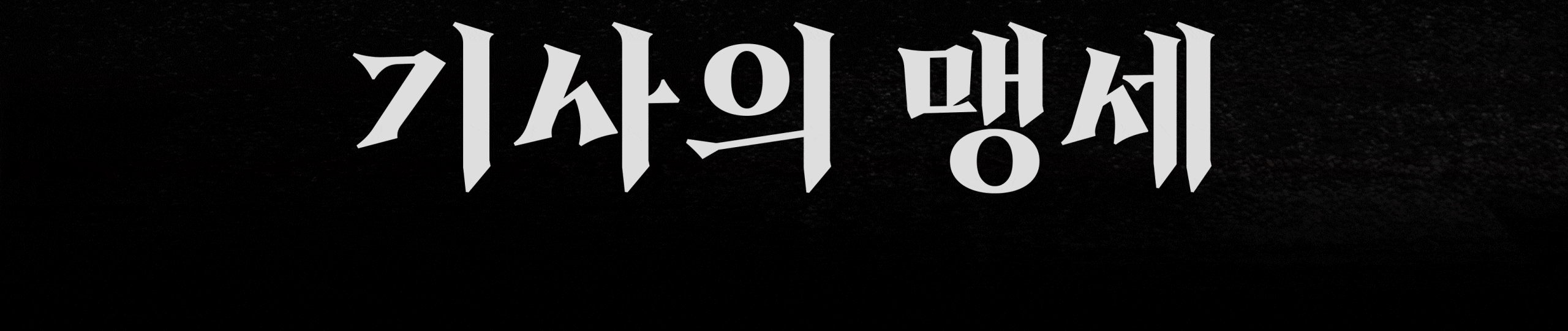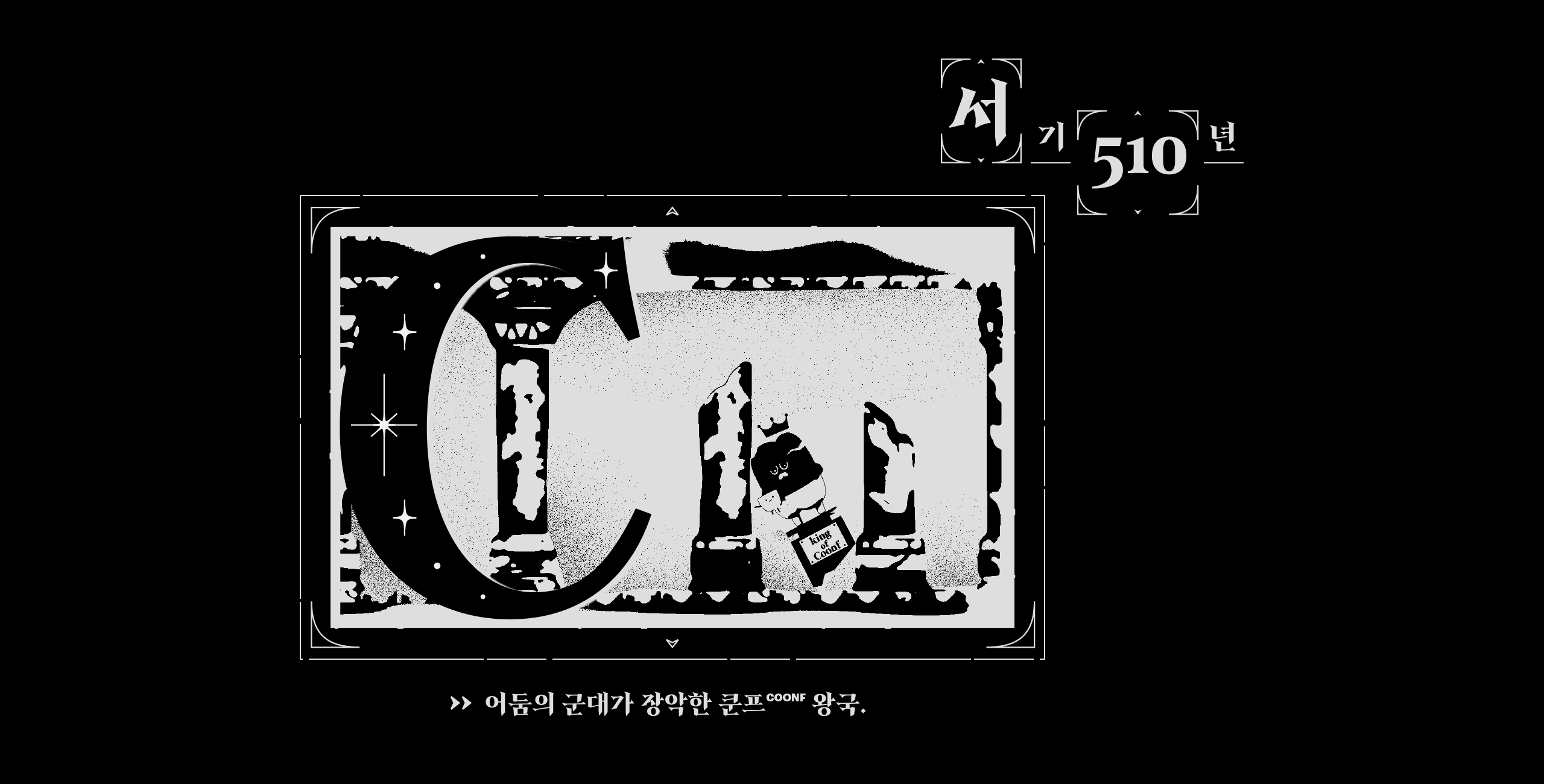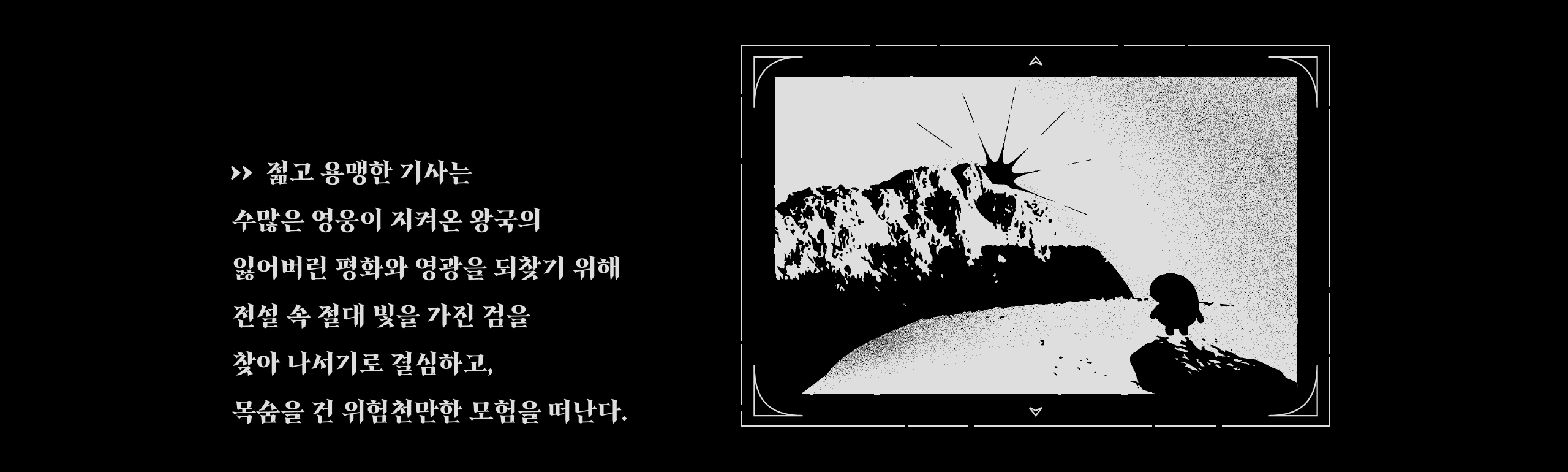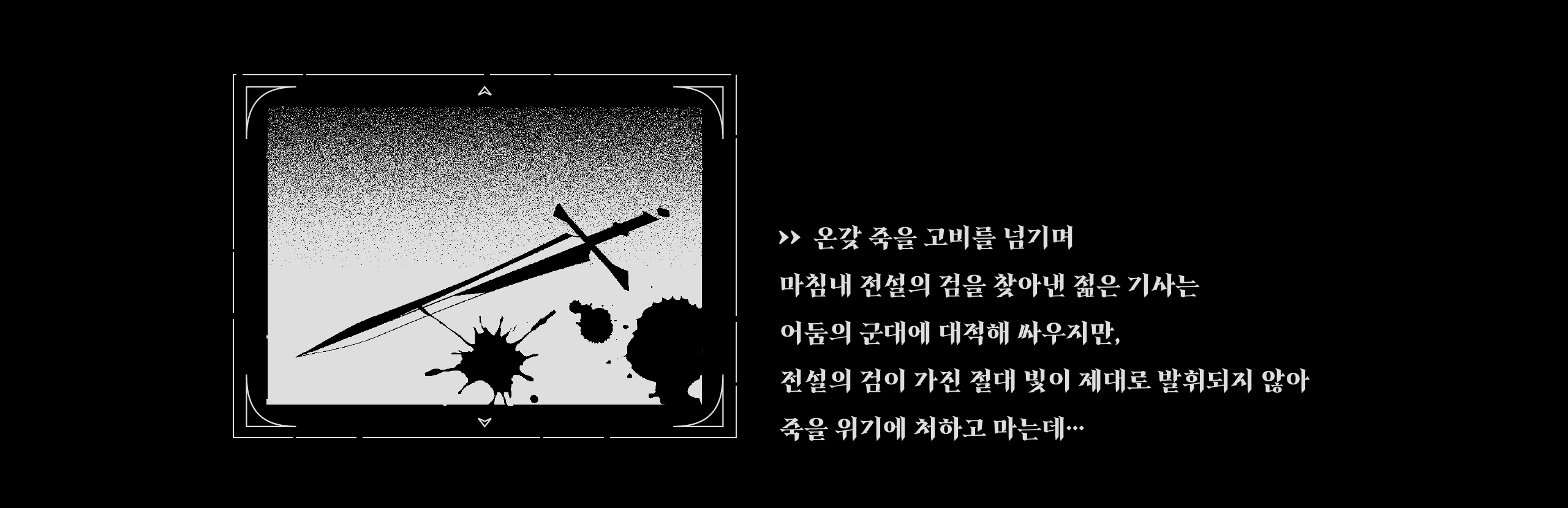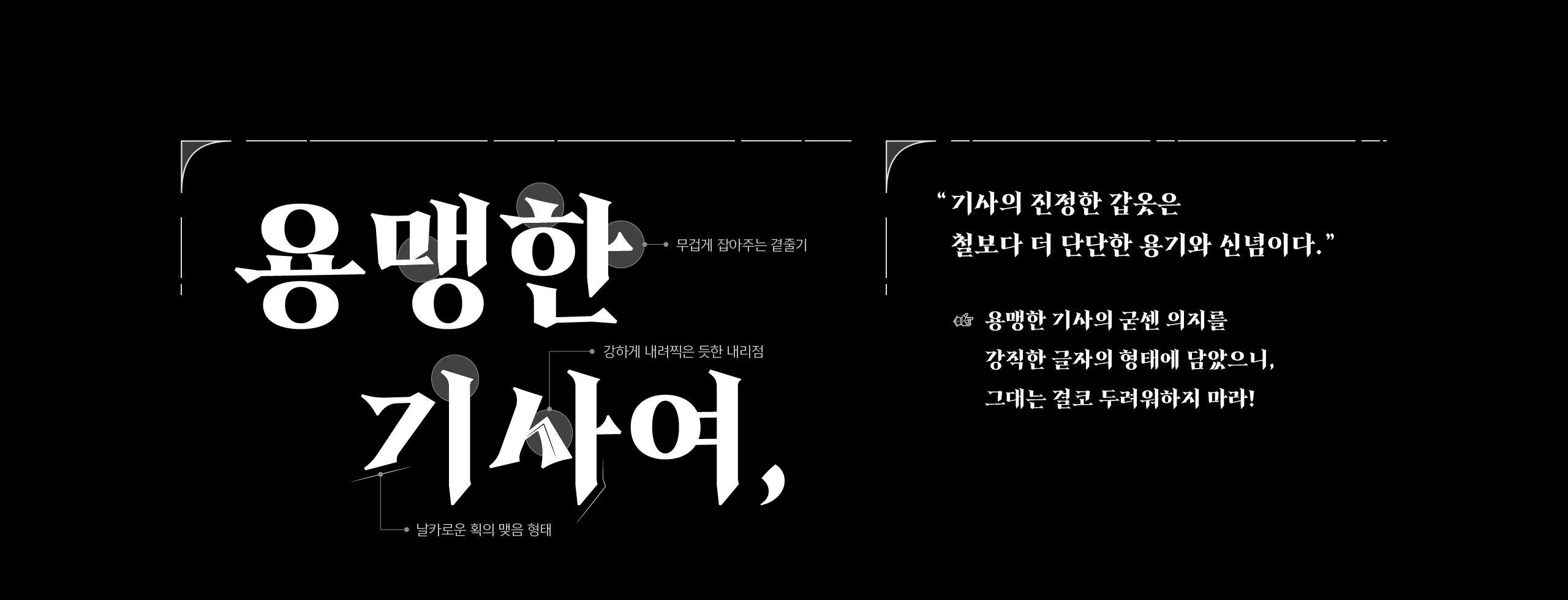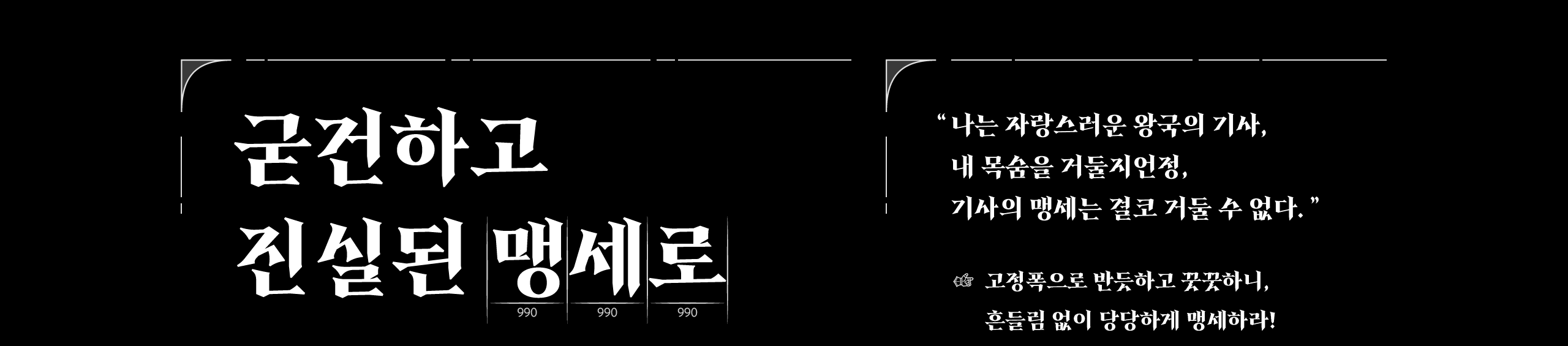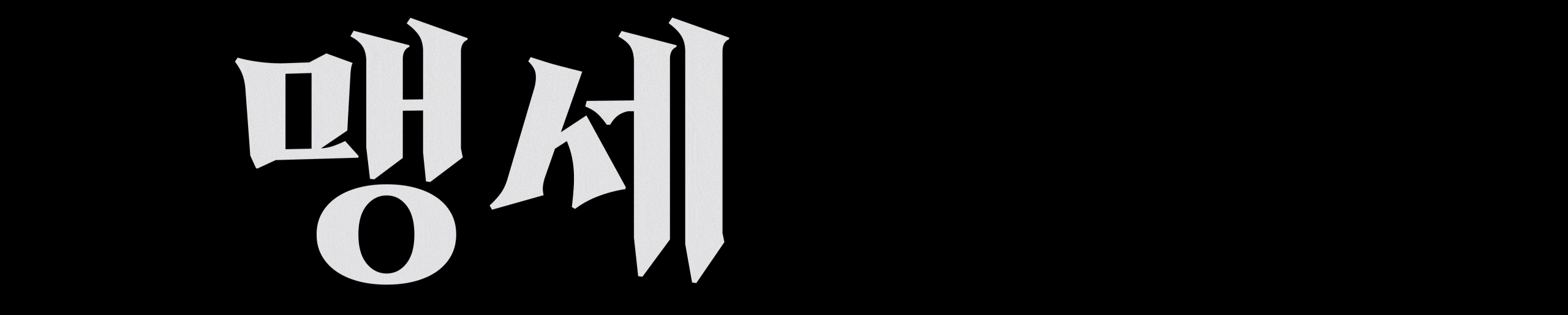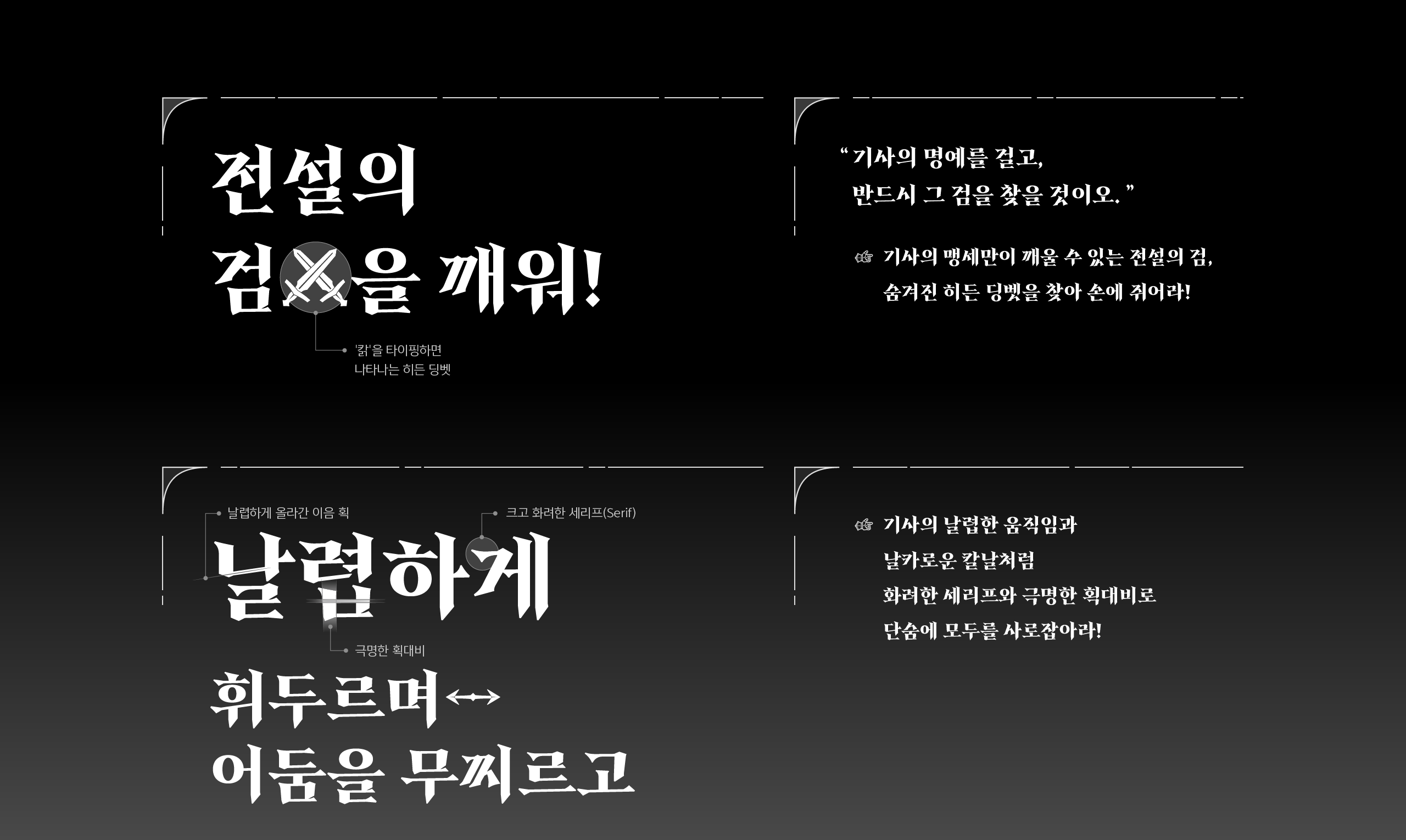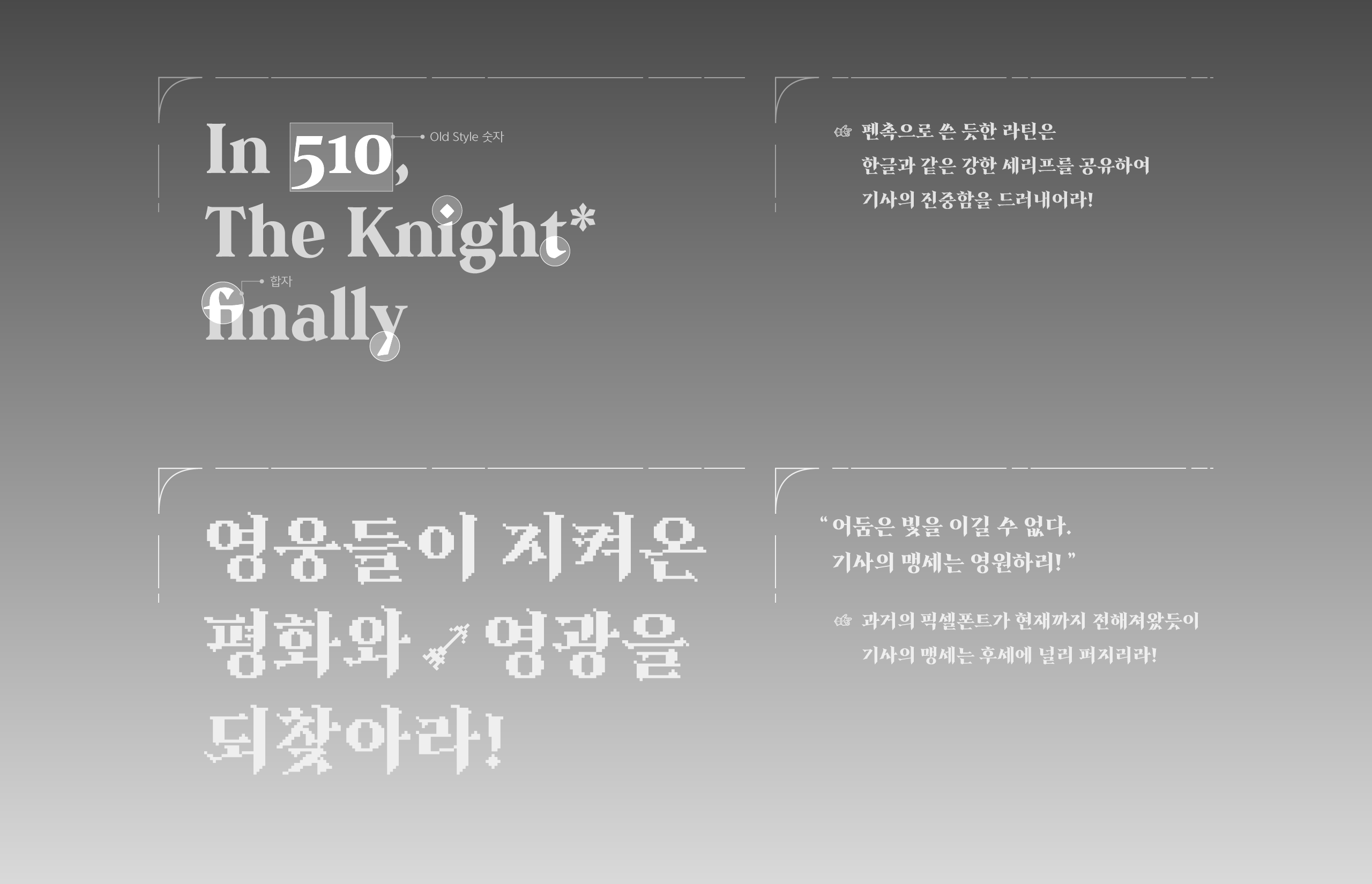
기사의맹세는 용맹한 기사의 굳건하고 진실된 맹세처럼 진중하고 강직한 느낌을 표현한 서체입니다. 화려한 세리프와 강하게 내려찍은 듯한 내리점, 날렵한 획과 극명한 획대비 등에서 예측 불가 스토리와 숨 막히는 액션, 상상 이상의 판타지가 머릿속에 펼쳐집니다. 세미볼드와 픽셀, 2종으로 구성해 활용성을 높였습니다.
Yoon 기사의맹세